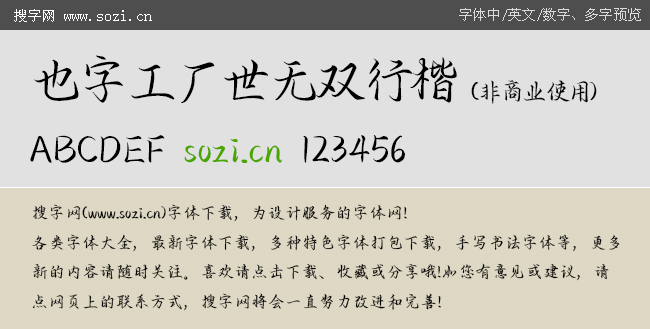
也字工廠世無雙行楷
搜字網(wǎng)給大家提供一款也字工廠世無雙行楷(非商業(yè)使用)中文字體下載,也字工廠世無雙行楷是一款手寫書法字體,字體書寫流暢,字形自然大方,具有很好的視覺效果。適合應(yīng)用于書籍畫冊(cè)、海報(bào)、網(wǎng)頁設(shè)計(jì)等應(yīng)用(此字體為個(gè)人非商用版,商用可以聯(lián)系:官方網(wǎng)址:https://yefont.com/home,聯(lián)系方式:13798980448)。